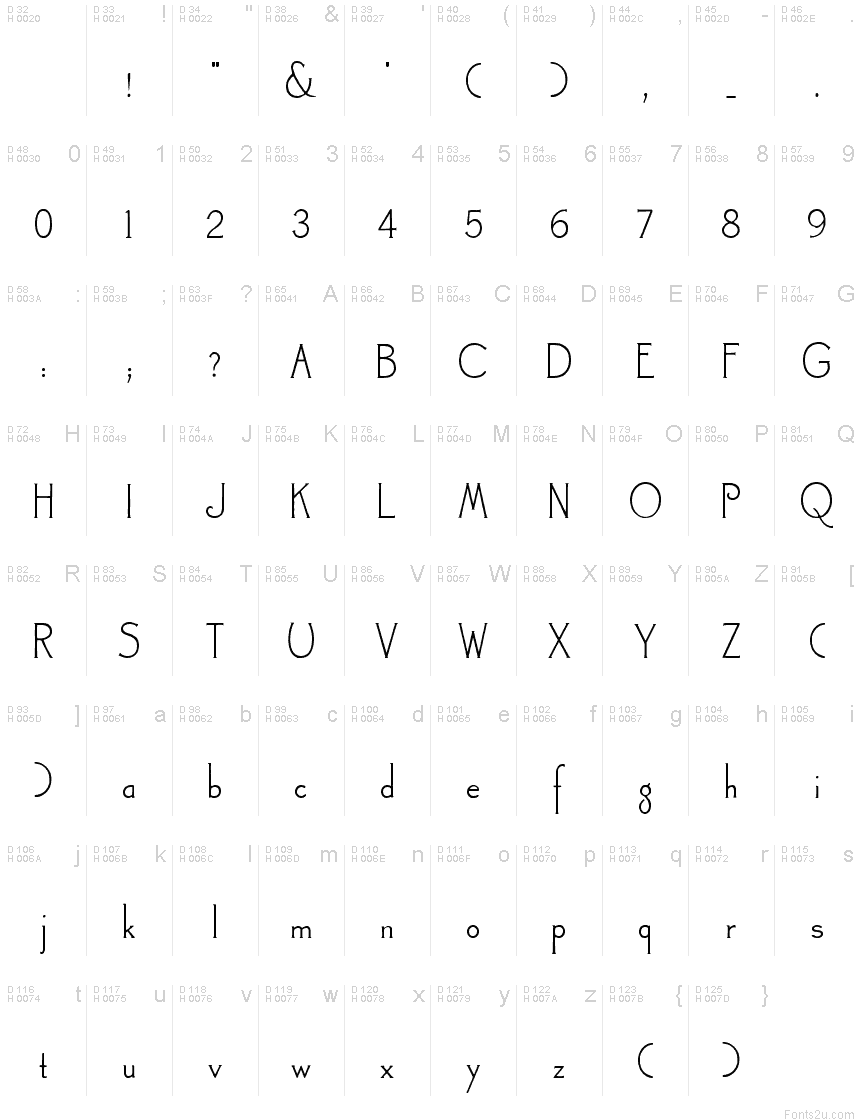
Landsdowne, zaprojektowany w 2002 roku przez PJL, to darmowy krój typu display w stylu retro o wysokiej, wąskiej sylwetce i delikatnie zaokrąglonych formach. Długie pionowe linie, otwarte kształty i powściągliwe krzywizny nadają mu spokojny, niemal znakowy rytm, który sprawia wrażenie bardziej przemyślanego niż dekoracyjnego.
Landsdowne doskonale sprawdza się w tytułach plakatów, etykietach opakowań, okładkach albumów, zaproszeniach i szyldach butikowych, wszędzie tam, gdzie przyda się smukły akcent retro. Jego kompaktowe kształty utrzymują krótkie nazwy w porządku na materiałach brandingowych, nagłówkach menu, cytatach redakcyjnych i projektach logo, zwłaszcza w układach jedno-wierszowych i na niewielkich oznaczeniach.